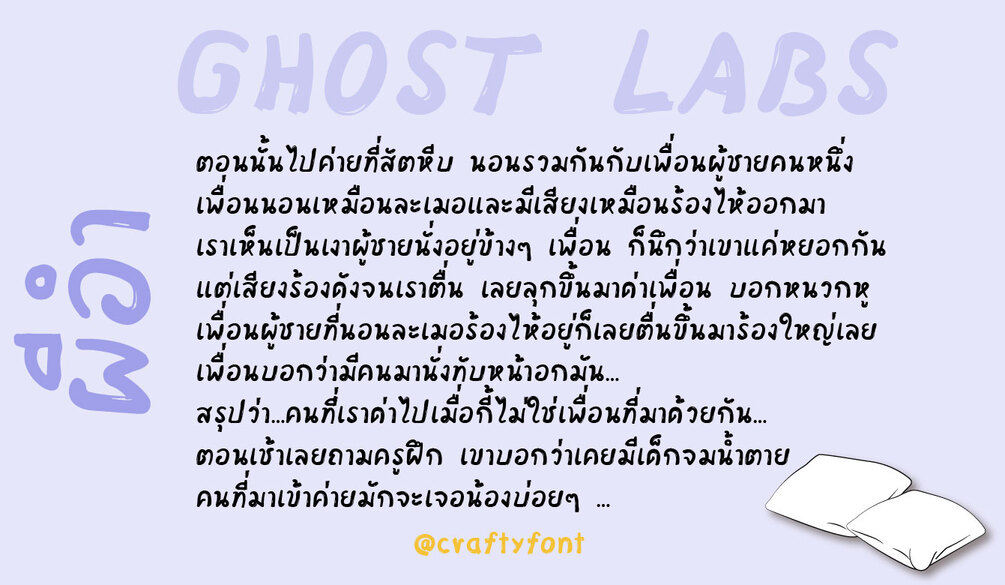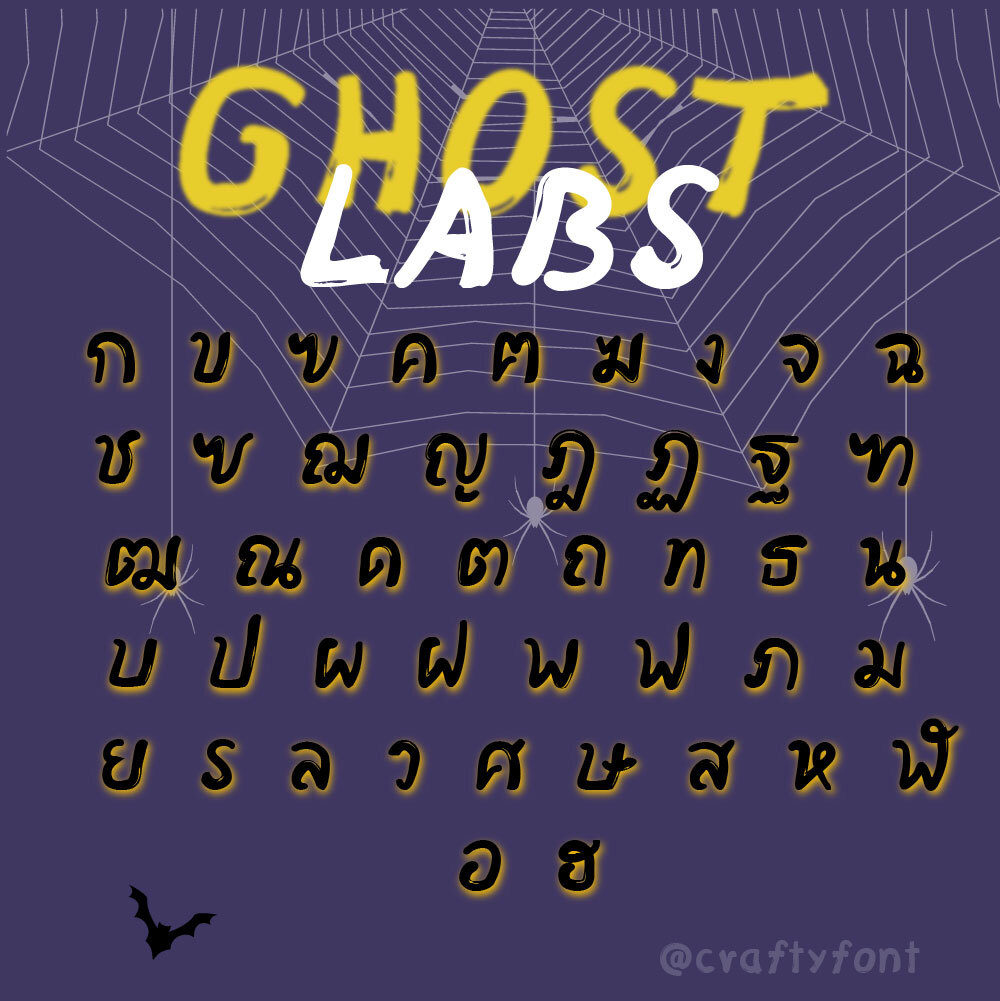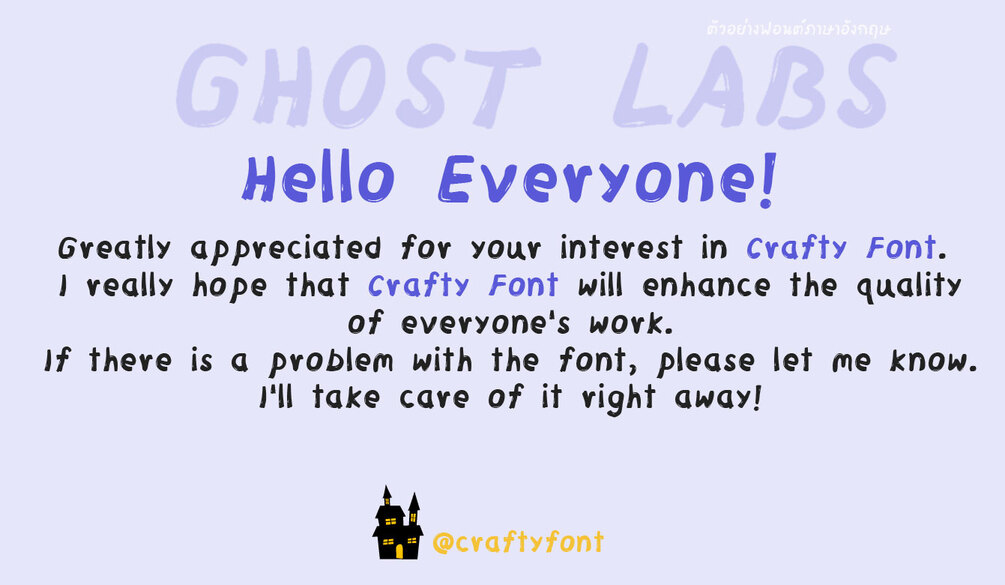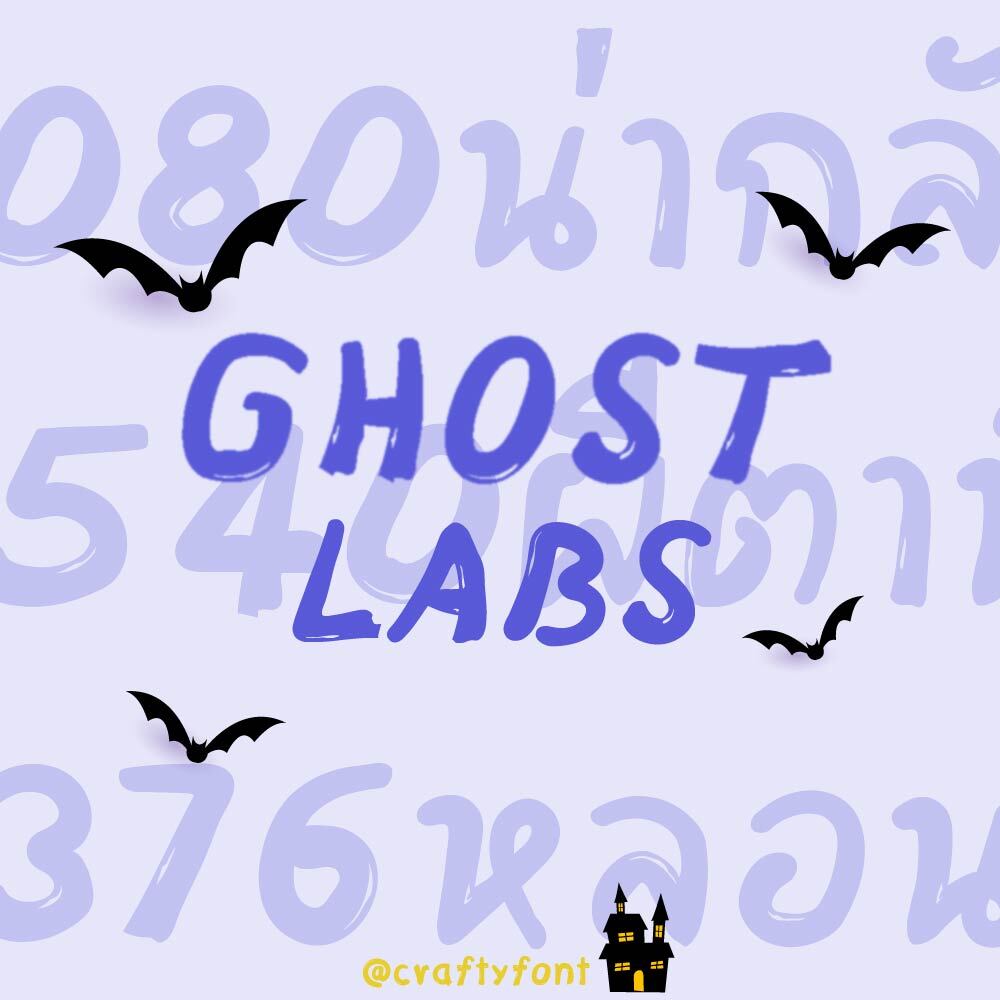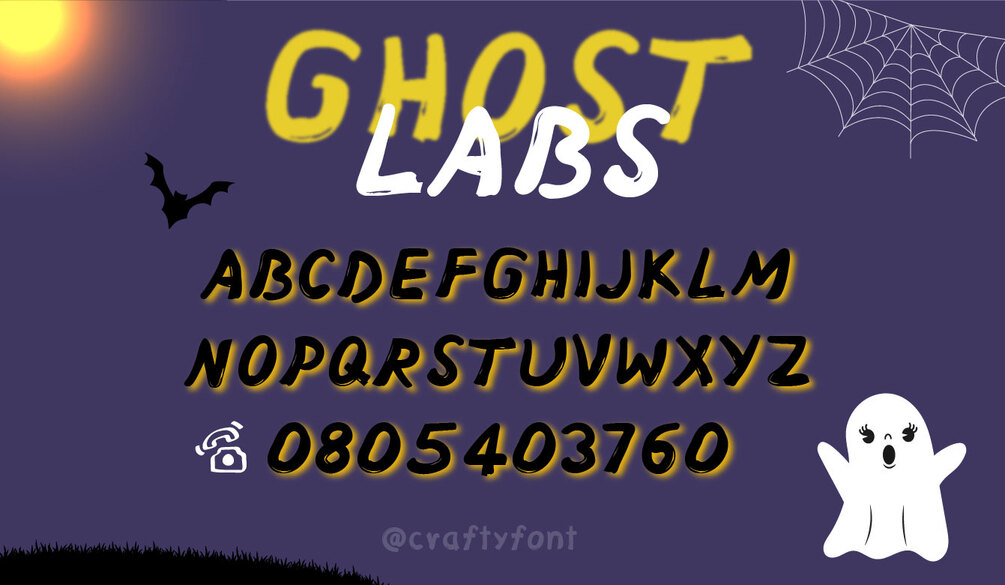
Ghost labs Font (ฟอนต์โกสแล็บ)
ฟอนต์ผีช่วงฮาโลวีน ผีน้อยน่ารักสไตล์ Crafty Font จะมาหลอกหลอนหัวใจคุณ 👻👻
ฟอนต์ Ghost labs มีทั้งภาษาไทยและภาษาอังกฤษ แฟมิลี่เซ็ตนี้มี 6 ขนาดด้วยกัน ทั้งตัวหนา ตัวปกติ ตัวบาง และตัวเอนสำหรับทุกน้ำหนัก สัญลักษณ์บวกลบคูณหารมีให้ใช้ครบ ฝากไว้ในอ้อมอกอ้อมใจพี่จ๋าด้วยนะจ๊ะ 🥰